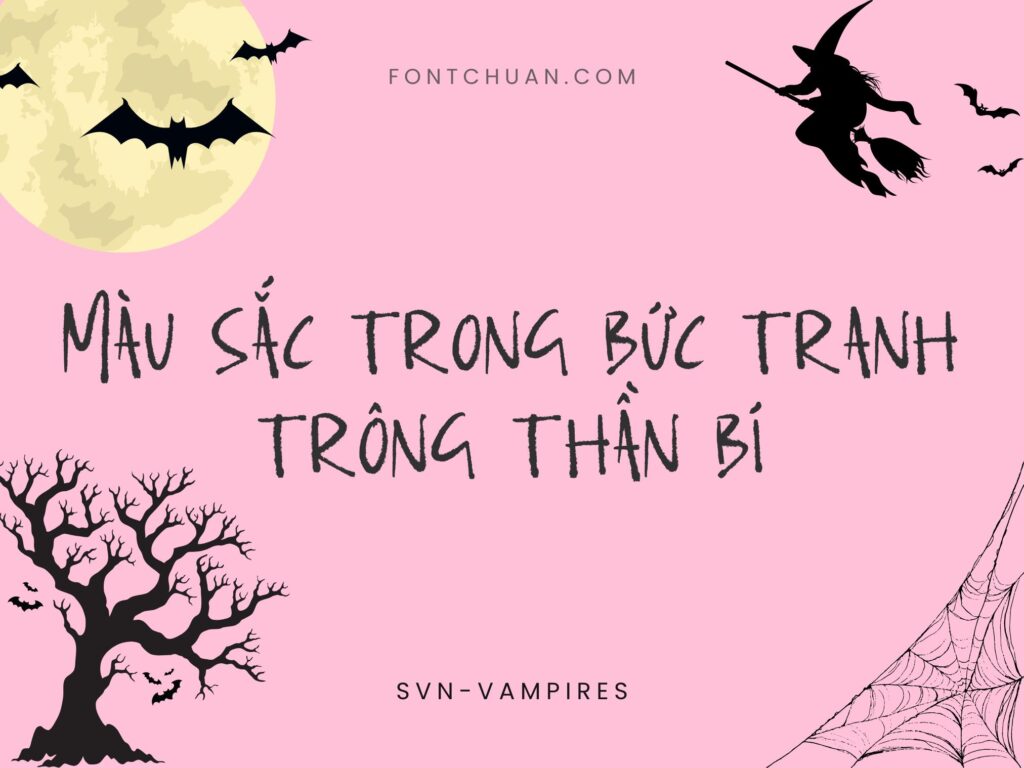
Font SVN Vampires Việt Hóa
Font SVN Vampires là phiên bản Việt hóa của kiểu chữ Vampires, được thực hiện bởi Styleno.1 Fonts. Vampires là một Font Decorative mang phong cách viết tay ma mị và huyền bí, tạo ấn tượng thị giác mạnh với các nét chữ phá cách và độc đáo. Font bao gồm đầy đủ ký tự chữ hoa, chữ thường, số và các dấu câu, hỗ trợ đa ngôn ngữ, giúp linh hoạt trong việc ứng dụng vào các thiết kế mang hơi hướng giả tưởng hoặc rùng rợn.
SVN Vampires đặc biệt phù hợp với các dự án cần sự phá cách như thiết kế tiêu đề, poster phim, bìa sách, hoặc các ấn phẩm quảng bá cho sự kiện đặc biệt. Các ngành nghề như quảng cáo, giáo dục hoặc công nghệ có thể ứng dụng để tạo điểm nhấn ấn tượng. Ngoài ra, font này cũng phù hợp cho các dịp như Halloween, Tết, Giáng sinh hoặc các lễ hội đặc biệt khác.